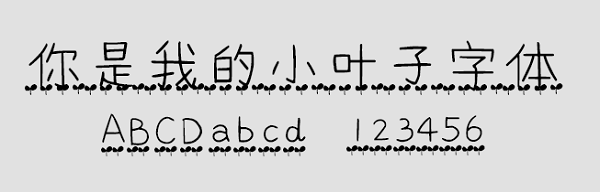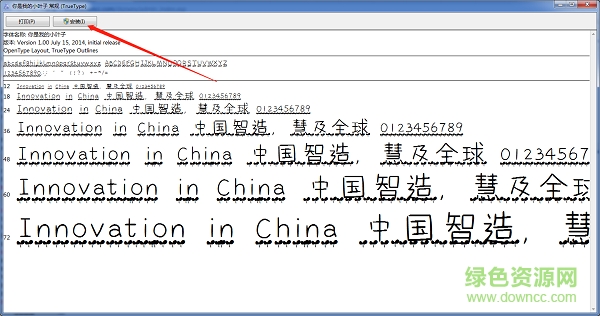
你是我的葉子字體是一款看起來充滿愛意的字體,每一個(gè)漢字,每一個(gè)字母下都設(shè)計(jì)有一個(gè)個(gè)小葉子,可愛又呆萌,讓字體整個(gè)看起來非常的獨(dú)特,自帶的特色給你更多新奇的感覺,喜歡的用戶快來綠色資源網(wǎng)下載吧!
你是我的葉子字體是一款非常漂亮的電腦中文字體,你是我的葉子擁有清新的字體外觀,由直線拼湊成的字體還融合的大量小葉子,小草和葉子連成一條線將漢字拖起來,非常清新,能夠支持漢字、符號(hào)、字母、數(shù)字等輸出格式,非常實(shí)用。
--手機(jī)字體是仿照兒童手寫風(fēng)格的卡通手寫字體,結(jié)構(gòu)帶有pop字體風(fēng)格!
--下面還配上了非常有趣的卡通圖案做襯線,特別適合喜歡個(gè)性字體的用戶使用編輯!